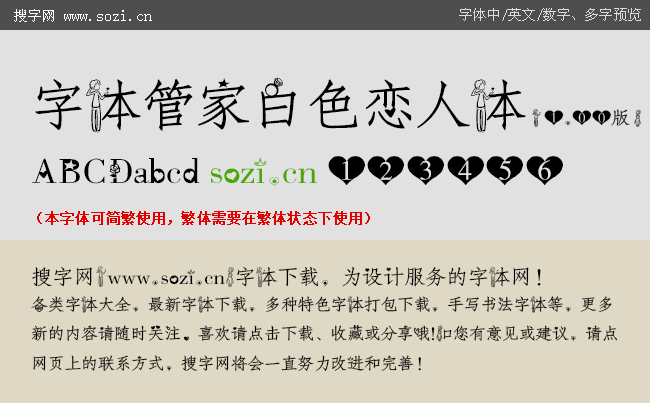
字體管家白色戀人體
搜字網(wǎng)給大家提供一款字體管家白色戀人體中文字體下載。字體管家白色戀人體是以宋體字體為原形。然后將個(gè)別筆畫換成了有趣的卡通圖形裝飾,適合兒童包裝,卡通畫冊(cè),海報(bào)設(shè)計(jì)等場(chǎng)合使用。
- 風(fēng)格類別: 美術(shù)圖形體